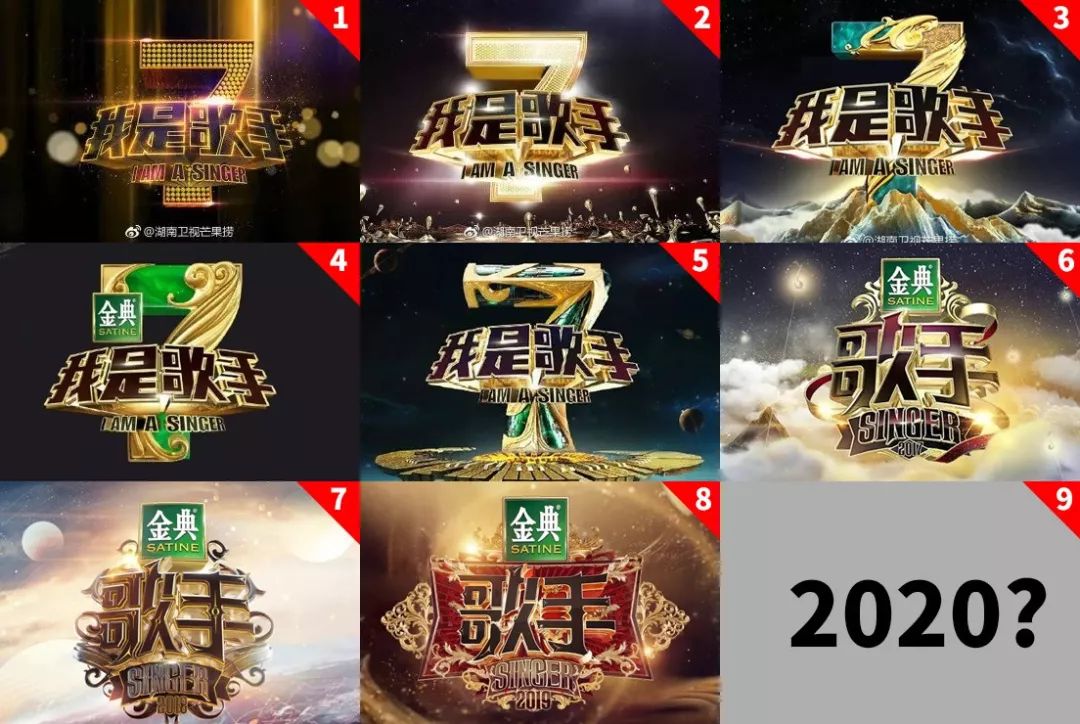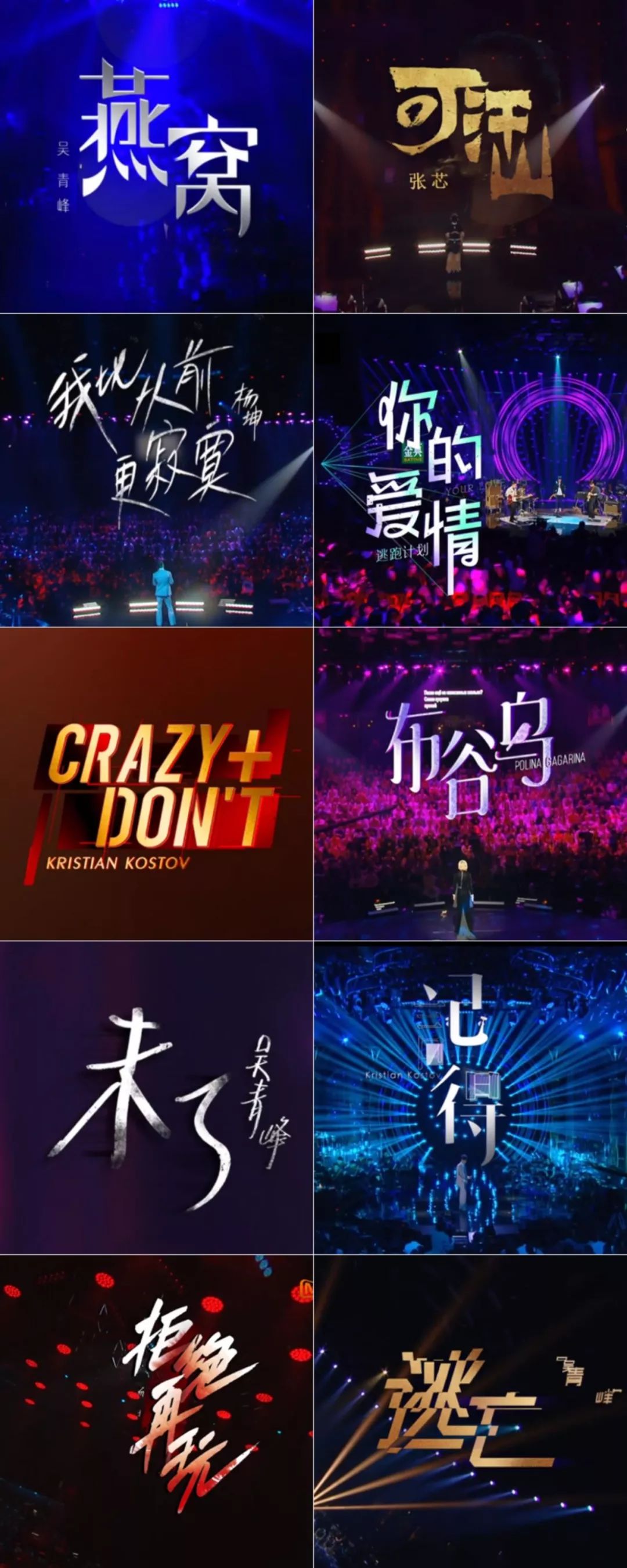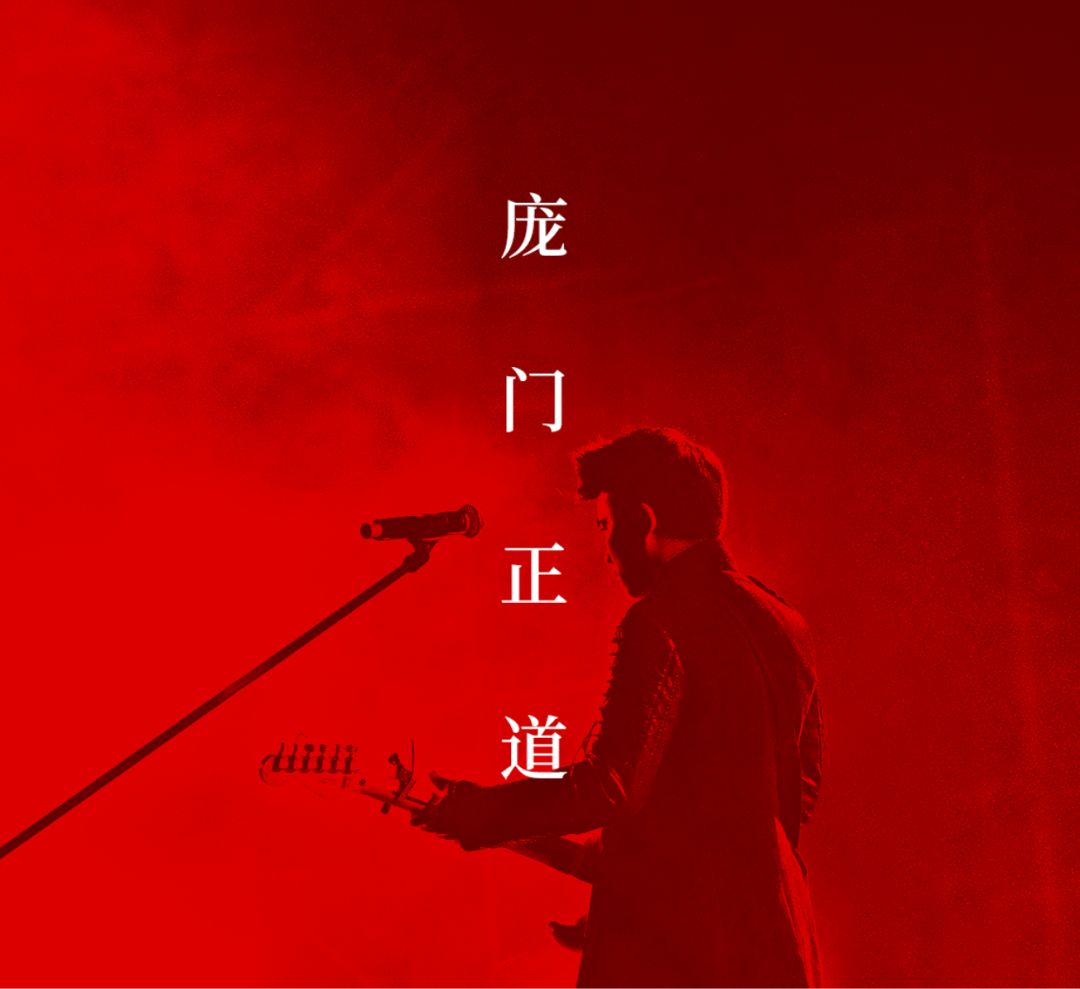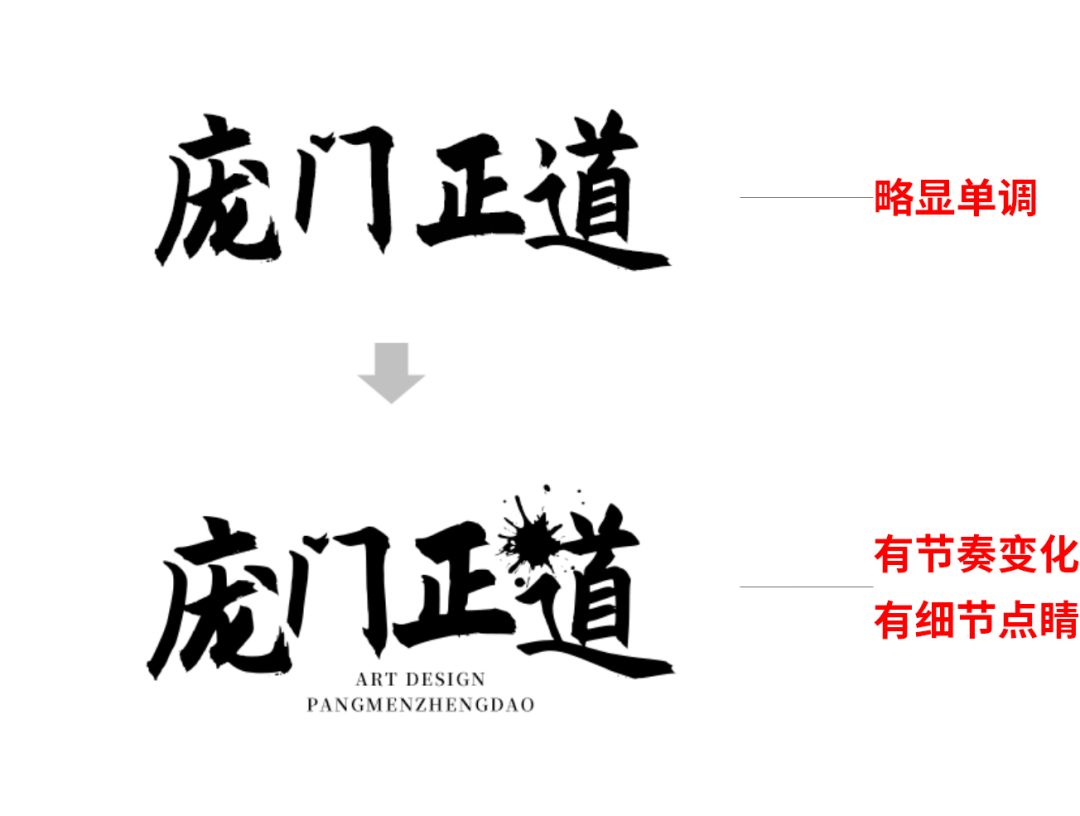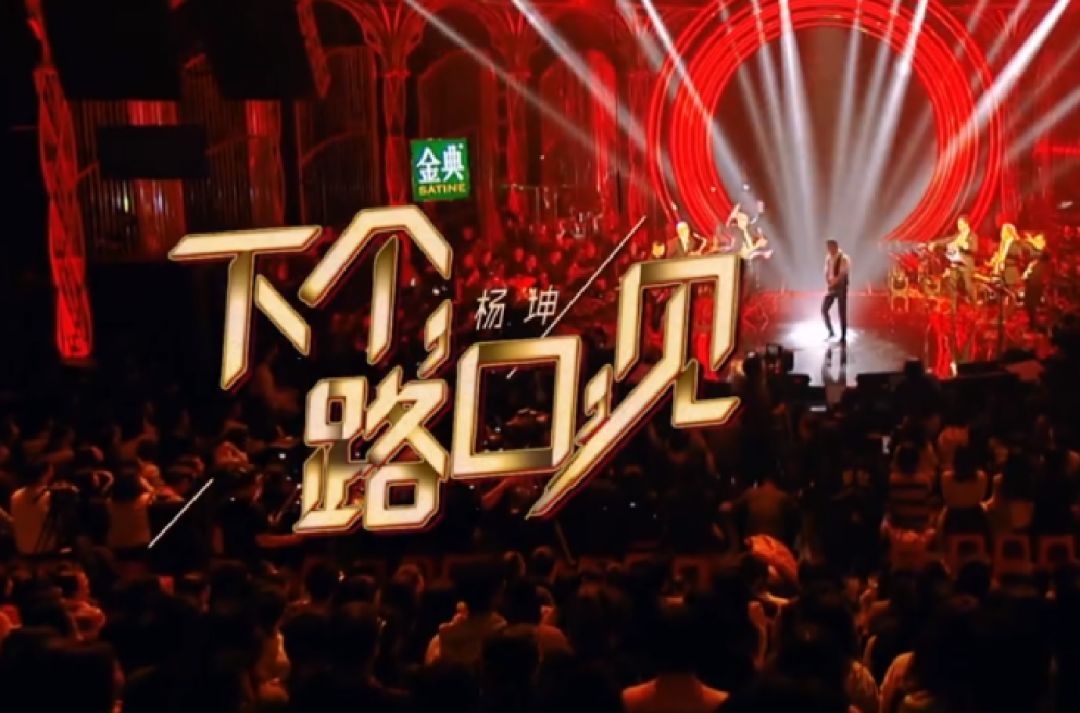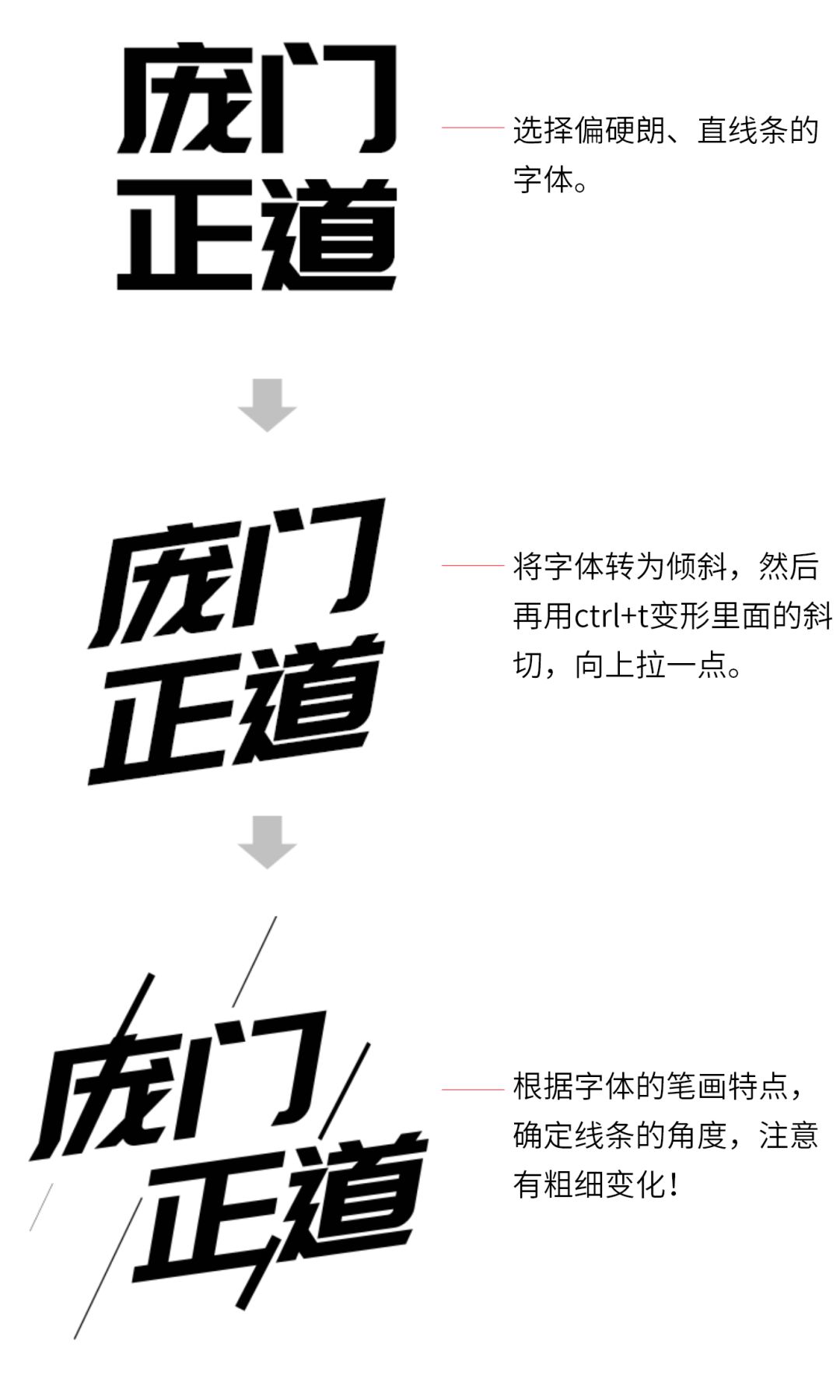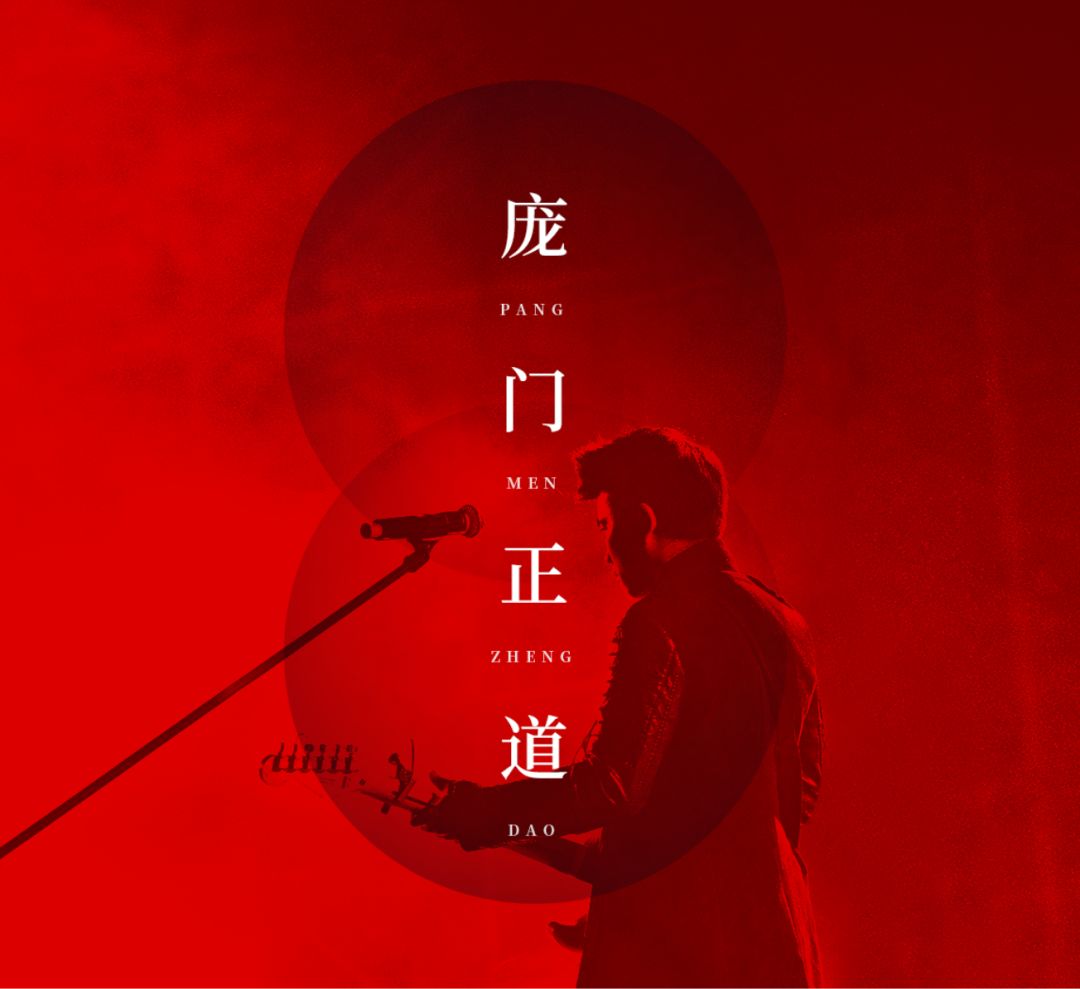
原来看《歌手》,也能学设计!
今年的《歌手》已经播了大半,我的感觉就是八仙过海,各显神通。刘欢-国家队选手、齐豫-元老级,这种大神级别的歌手都请过来了,真不知道下一季还能怎么玩。当然,有可能就是没有下一季了。
管它有没有下一季,看一期算一期,而我在这一季的最大收获是,认识了“声入人心”,算是划算了。
当然,这些不是我们这些吃瓜群众操心的。关于这一季的《歌手》,我想说的是:它不一定是最好听的一季,但一定是目前最“好看”的一季!
怎么个好看法?我慢慢给你分析。
在看了几期节目之后,我简直被《歌手2019》的各种视觉包装震撼了!
请注意,是各种!
从舞台灯光,到视频制作,再到歌手海报,各种惊艳。
芒果台真的是不惜血本!
如果用一句话来形容这一期的视觉包装,那就是:武装到牙齿。
好了,废话不多说,直接上图。
不知不觉,我们已经经历了8年的《歌手》,是不是没想到?模糊印象中只有4-5年的样子,没想到都8年了。
我们从第一代的logo到现在的logo,当然是看到很大的进步,但是是不是最新的就是最好的呢?不一定。技术一直在进步,但是审美并没有。
先看看最新的LOGO。
这个LOGO视觉上肯定是没得说,质感精细得令人发指,动画过度也很舒服,不过由原先的圆形变成了方形,可能有些人一时间还有点适应不了。
另外这个缕空雕花的风格,我怎么看着有点眼熟呢?
结果在打开淘宝的时候我找到了答案:
莫非,难道,灵感是来自于欧式家居?
算了算了,中国人用欧式花纹多数都是有点乱用的感觉的了。
还是看海报设计吧!
海报还是像以往那样,有几版不同的风格,我每版只放两张示意。
这次的海报并没有像以往那样追求艺术化,而是多了几分朴实。这可能是暗示着这次要返朴归真,更加追求音乐性,希望各位歌手在选曲上勇敢做自己。
尤其是是亮出眼睛部分的这系列,可以说是非常的巧妙了。
相对2018年和过往的很多期,依然还在进步。
2018年这2组,设计的表现力很好,但是有点弱化艺人本身。
上面这些都是常规操作对吧?接下来我们来看下不常规的。
电影级的片头剪辑
这季的《歌手》有个简短的片头,像电影一样的,先是呈现出整个节目的主创团队。
然后是歌手,以及其音乐理念的介绍。
最后的定帧是当前一集的音乐主题。
首集播出的时候,我当时就被这个场景给震撼住了,宏大肃穆,仪式感十足,让人感受到节目组对于艺术的敬畏之心。
这个精致的片头,排版大气,视效丰富,寓义深远,说是电影级也毫不为过。
我们再来看看对每首歌曲的包装。
唱片级的曲目包装
片头部分已经是十分精彩,再看看对歌曲的包装,你会发现,设计师的用心程度简直令人发指。
每首歌的歌名报幕:
完全是视觉盛宴啊有没有?!
随便一张拿出去当专辑封面,都完全没压力。
我相信节目组肯定是要求对每首歌曲的包装,都完全是按照唱片的标准来出效果的。
除了歌名,歌曲信息的展示也体现了设计师深厚的功底,每首歌的歌曲信息都根据歌曲风格、画面构图,做了相应的视觉风格匹配。
丧心病狂的要求,不过这个也是有追求的表现,很感谢他们的用心,提升普通国民的审美标准。
是不是和唱片的包装手法十分的像?
来看看五月天的CD包装设计:
虽然说综艺节目只是娱乐快消品,很显然芒果台打造了一个非常极致的快消品。
作为一个设计师,我们当然不能只看热闹,不看门道。
那接下来我们就看看这些设计里面有哪些是值得我们“偷师”的。
一、活用小字、点缀元素,丰富排版。
比如说下图的字幕展示,很简单的一个排版,但是加了小字和音符元素之后,档次马上就大大的提升。
这张图也是一样,里面用到了很多种点缀、穿插的小元素,使得排版的视觉层次很丰富。
再来看看我之前做过的案例,庞门正道的文字下加了一点小字,一点小小的改动,就让标题没那么单调了。
最后来一个简单实用的案例,首先书法字体打上文案,然后做一点大小变化,细节上再加点墨渍与小英文,一个LOGO雏形就此诞生。
这招其实在排版中非常实用,值得大家慢慢推敲。
接下来我们看第二招。
二、利用线条,增强动感与空间感。
比如下面这张图,一束放射型的线条就可以使得画面有很强的纵深感。
不同粗细、长短的线条,形成了前后关系,使得大色块显得没那么呆板。
红色的线条不但让画面更有动感,同时也丰富了文字的肌理。
倾斜向上的线条会让人感觉动感十足。
自己动手做一个示范案例:
简短的三步,一个非常运动感的字体效果就生成了。
是不是既简单又实用!
好了,继续往下看。
三,添加色块,增强层次感。
文案背后的色块,既加强了文字的辨别度,也让画面更有层次感。
倾斜的色块+线条,和整首歌的动感节奏搭配得很好。
在文案下面叠两个小圆圈,让画面看起来更精致了。
再来看一下我自己做的案例:
还是这张图,虽然照片够帅,但是直接把文字压上去会显得稍微有点突兀,没有跟照片形成呼应关系。
按照我们上面讲到的方法,我们先添加上小字,然后在文字背景叠加两个圆形,这样是不是就好多了呢?
或者也可以试下更加犀利的三角形:
效果是不是棒棒的,拿去做CD封面妥妥的!
讲到这里你会发现,其实他们用的设计手法都是非常基础的,关键是用得恰到好处!
所以我们做设计的,别总想着憋个大招,搞个大新闻,把各种排版的基本功练扎实了,就够应付绝大多数工作了。